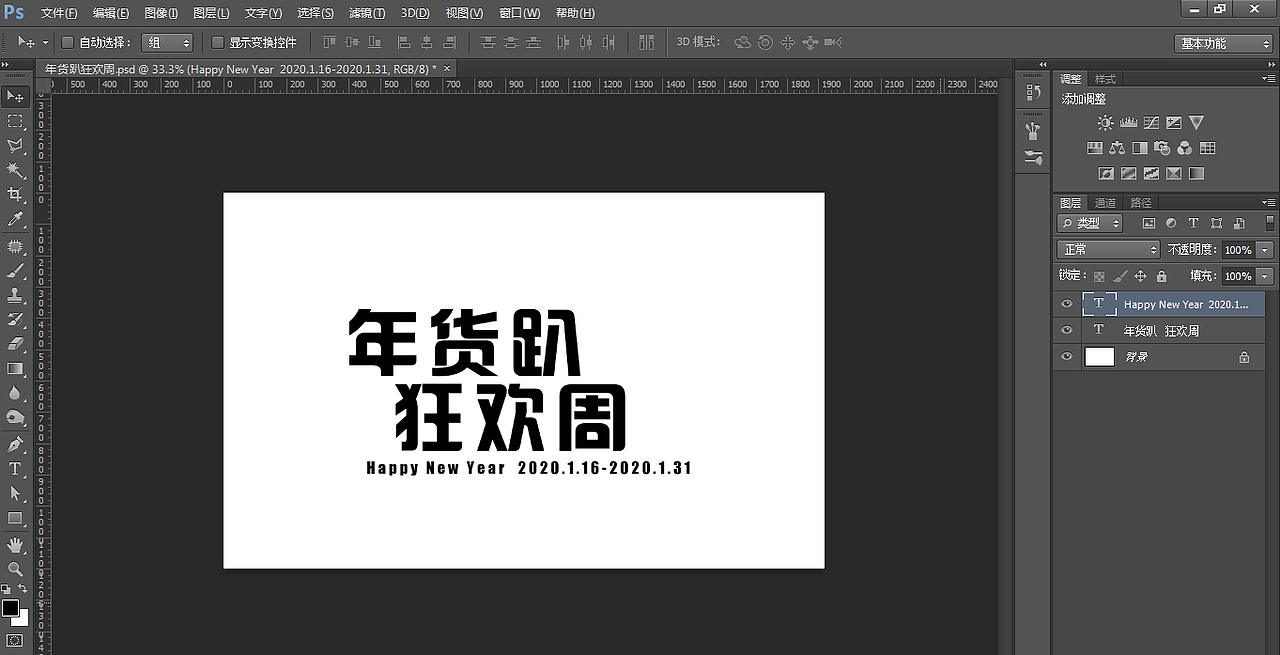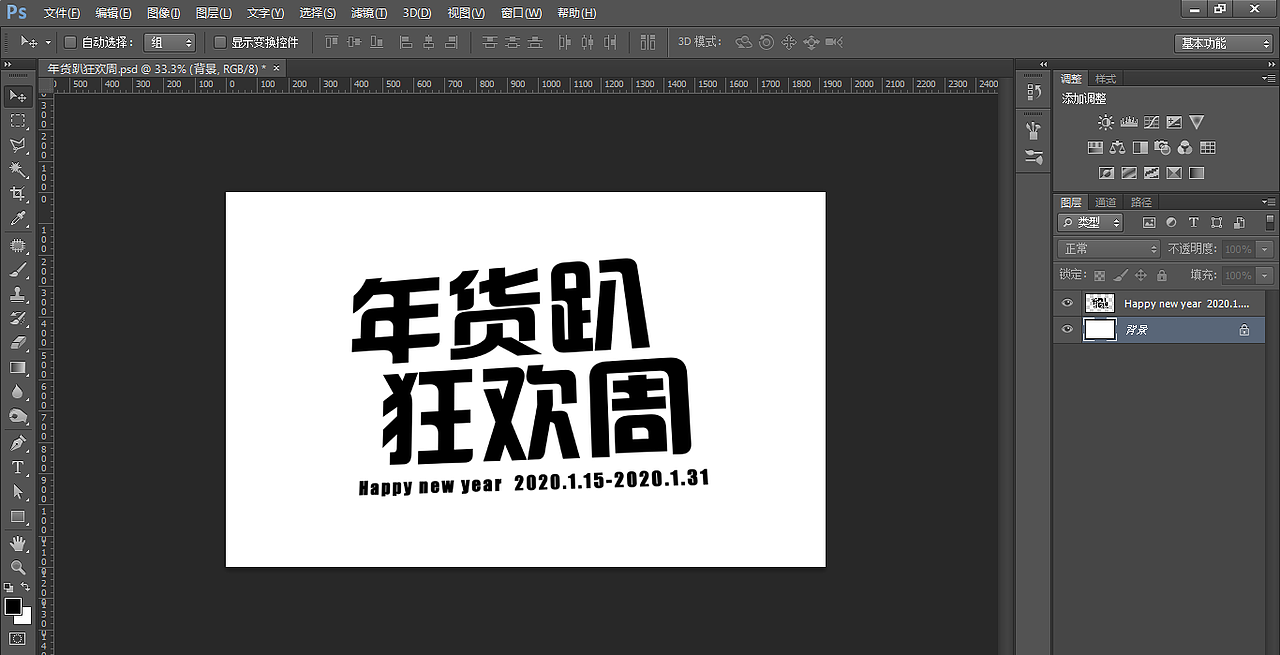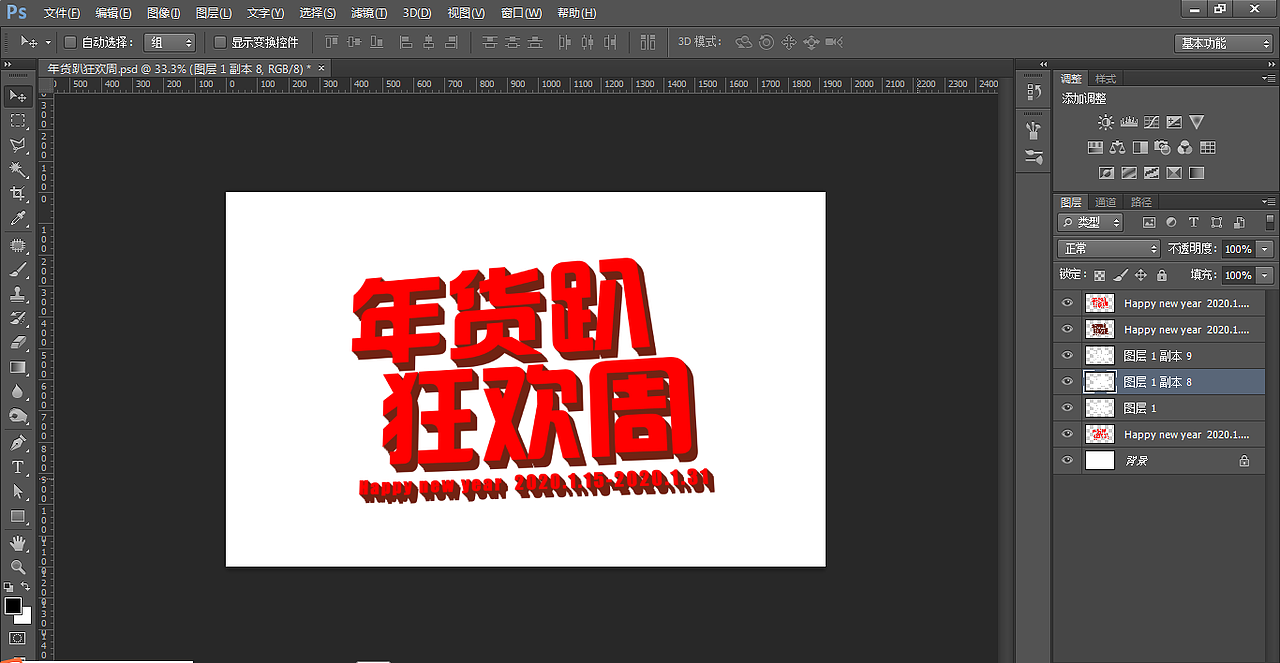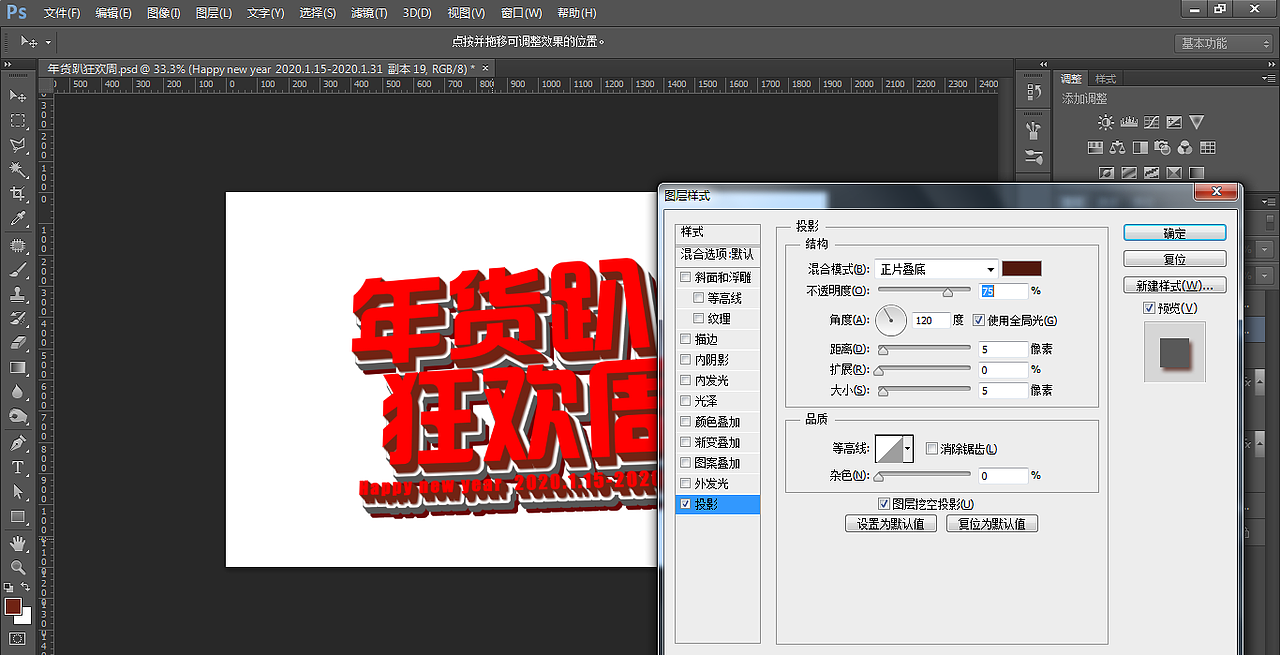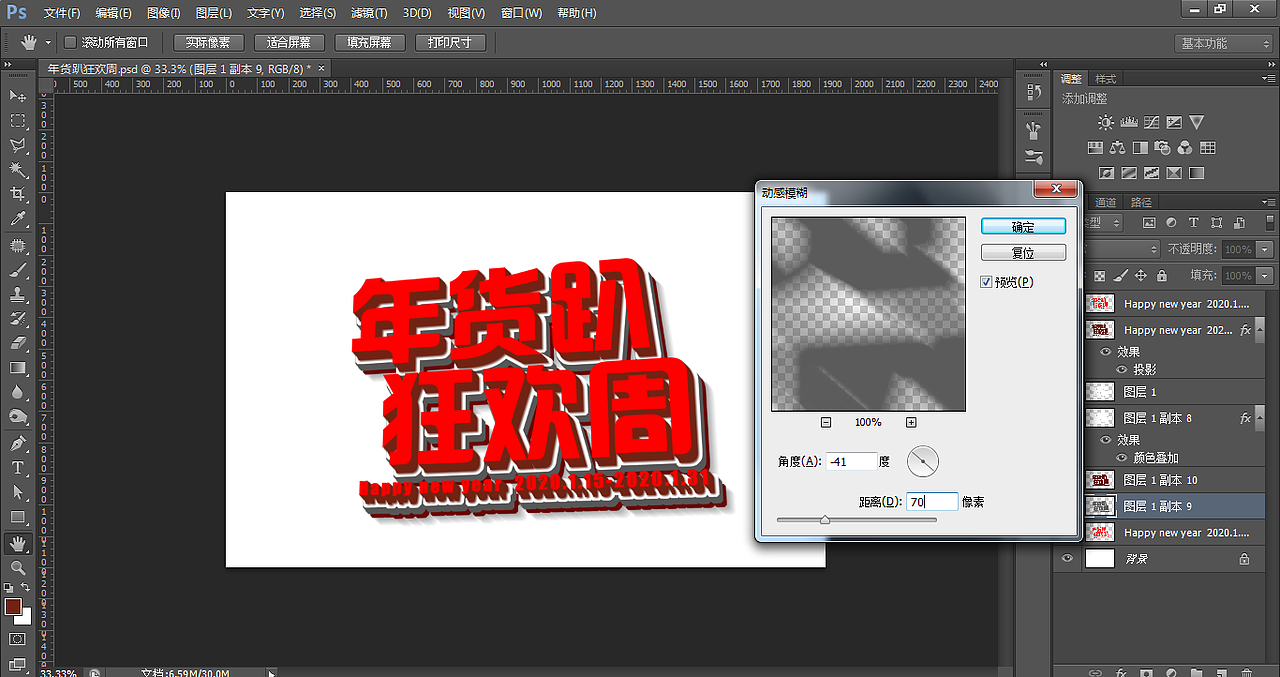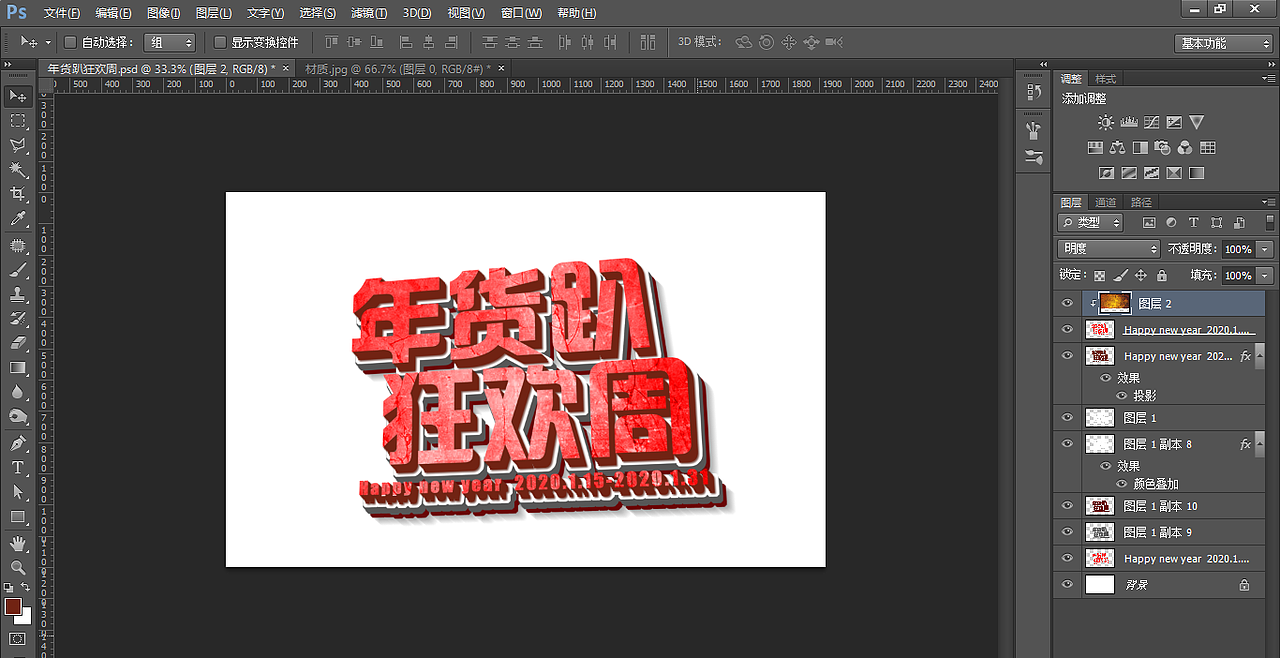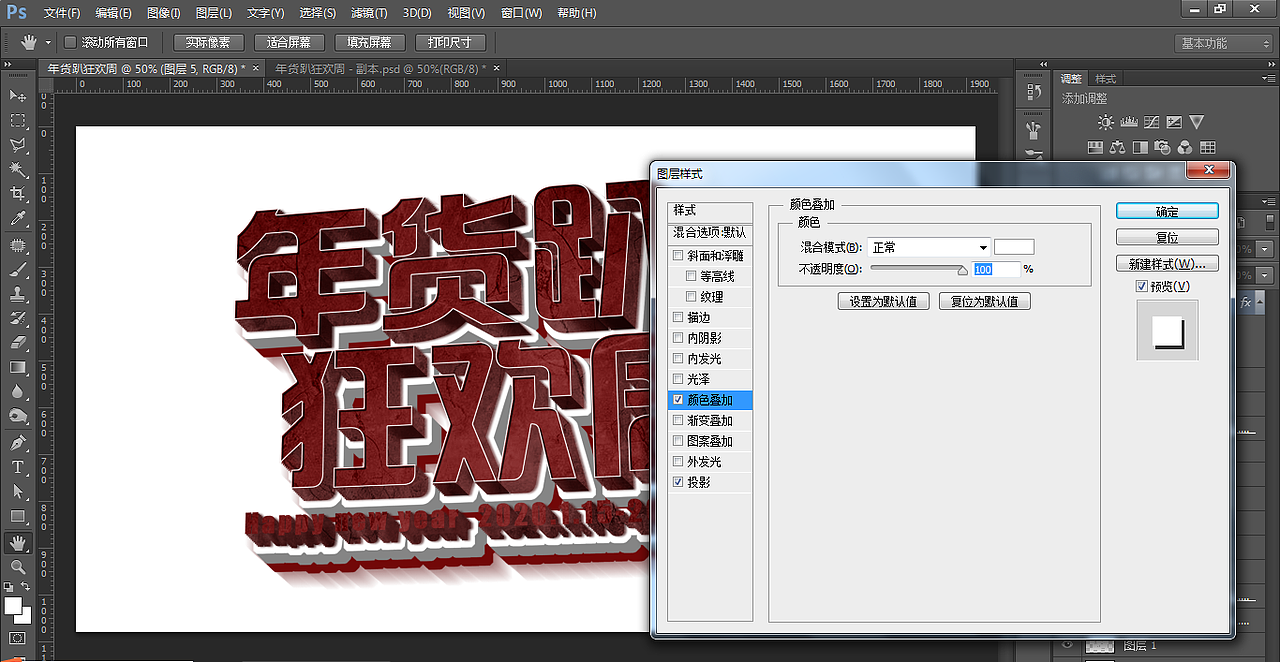
字体设计_PS-立体年货趴狂欢周
多层次立体字制作
重点:
1.明暗部分的绘制
2.图层样式与画笔的应用
难点:
1.立体面明暗部分的把控
2.立体面棱角的处理
3.立体面材质的处理
这种字体类型特效比较适合节日活动页面
1、【打开】PS软件,【新建】任意大小的画布。具体效果如图示。
2、使用【文字工具】,【字体】迷你汉真广标,依次输入文字,调整文字大小和间距,排列至画面合适的位置。具体效果如图示。
3、【修改】英文字体,【选择】关联文字图层,按【Ctrl+T】自由变换,按Ctrl键拖动一边倾斜至合适的角度。【选择】两个文字图层,按【Ctrl+E】合并图层,按【Ctrl+T】自由变换,按Ctrl键拖动锚点调整文字至合适的形状。具体效果如图示。
4、打开【图层样式】-【颜色叠加】,具体参数如图示。具体效果如图示。
5、按Alt键加方向键【向下移动复制】至合适的次数,【选择】中间关联图层,按【Ctrl+E】合并图层,调整图层顺序。具体效果如图示。
6、【选择】立体文字图层,打开【图层样式】-【颜色叠加】,具体参数如图示。具体效果如图示。
7、按Ctrl单击底部文字图层【载入选区】,单击【选择】-【修改】-【扩展】12PX,【填充】白色。按Alt键加方向键【移动复制】合适的次数,【选择】中间白色关联图层,按【Ctrl+E】合并图层,调整图层顺序。具体效果如图示。
8、【选择】白色底部文字图层,打开【图层样式】-【颜色叠加】,具体参数如图示。具体效果如图示。
9、右击【栅格化图层样式】,按Alt键【拖动复制】灰色立体层至合适的位置,调整图层顺序,打开【图层样式】-【颜色叠加】,具体参数如图示。具体效果如图示。
10、【选择】顶部深色立体图层,打开【图层样式】-【投影】,具体参数如图示。具体效果如图示。
11、按Alt键【拖动复制】图层样式至对应的文字图层,调整图层顺序。【复制】深灰色立体图层,打开【图层样式】-【颜色叠加】,具体参数如图示。具体效果如图示。
12、调整图层顺序至底部,单击【滤镜】-【模糊】-【动感模糊】,具体参数如图示。具体效果如图示。
13、调整文字颜色细节和大小,移动至合适的位置。【拖入】材质素材,调整大小和形状,置于表层文字上方合适的位置,按Alt键单击【创建剪切蒙版】,【图层模式】明度。具体效果如图示。
14、按Alt键【拖动复制】材质图层,右击【栅格化图层】。按【Ctrl+Shift+U】去色,【图层模式】正片叠底,调整图层顺序至合适的图层上方,按Alt键单击【创建剪切蒙版】。具体效果如图示。
15、【新建】剪切蒙版图层,【图层模式】柔光,使用相同的方法绘制立体字的亮部区域。具体效果如图示。
16、按Ctrl单击顶部文字图层【载入选区】,使用【套索工具】,按Alt键【减去】多余的文字选区。【新建】图层,按【Alt+E+S】内部描边3PX。打开【图层样式】-【颜色叠加】,具体参数如图示。具体效果如图示。
17、添加【投影】,具体参数如图示。具体效果如图示
18、在顶部材质图层上方【新建】剪切蒙版图层,【图层模式】柔光,使用【画笔工具】,【颜色】白色,调整画笔属性和大小,在合适的位置单击。具体效果如图示
19、使用【画笔工具】,【颜色】白色,调整画笔属性和大小,在狂字上方单击,【不透明度】60%。具体效果如图示。
20、【拖入】闪光素材,放置文字上方合适的位置。【图层模式】明度,【不透明度】77%。具体效果如图示。
21、【选择】所有关联图层,按【Ctrl+G】编组,按【Ctrl+T】自由变换大小,排列至画面合适的位置,调整画面整体细节,可适当提亮,最终效果如图示